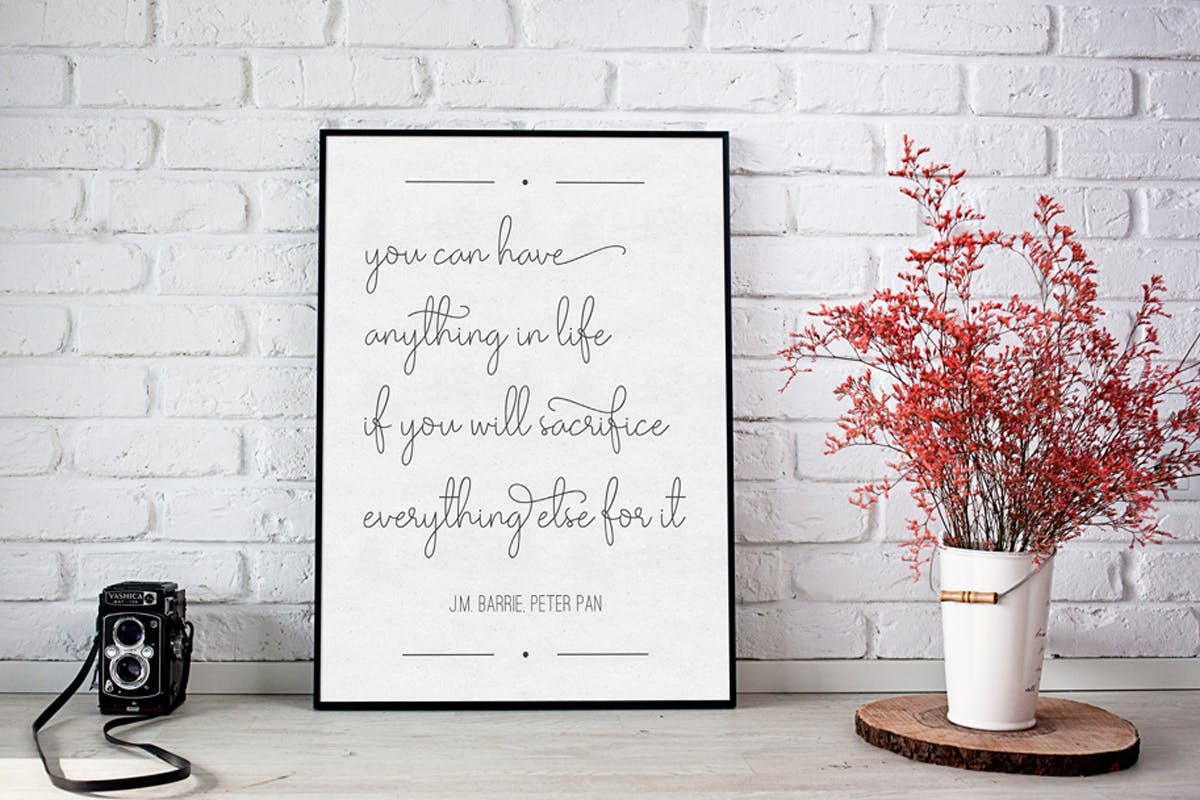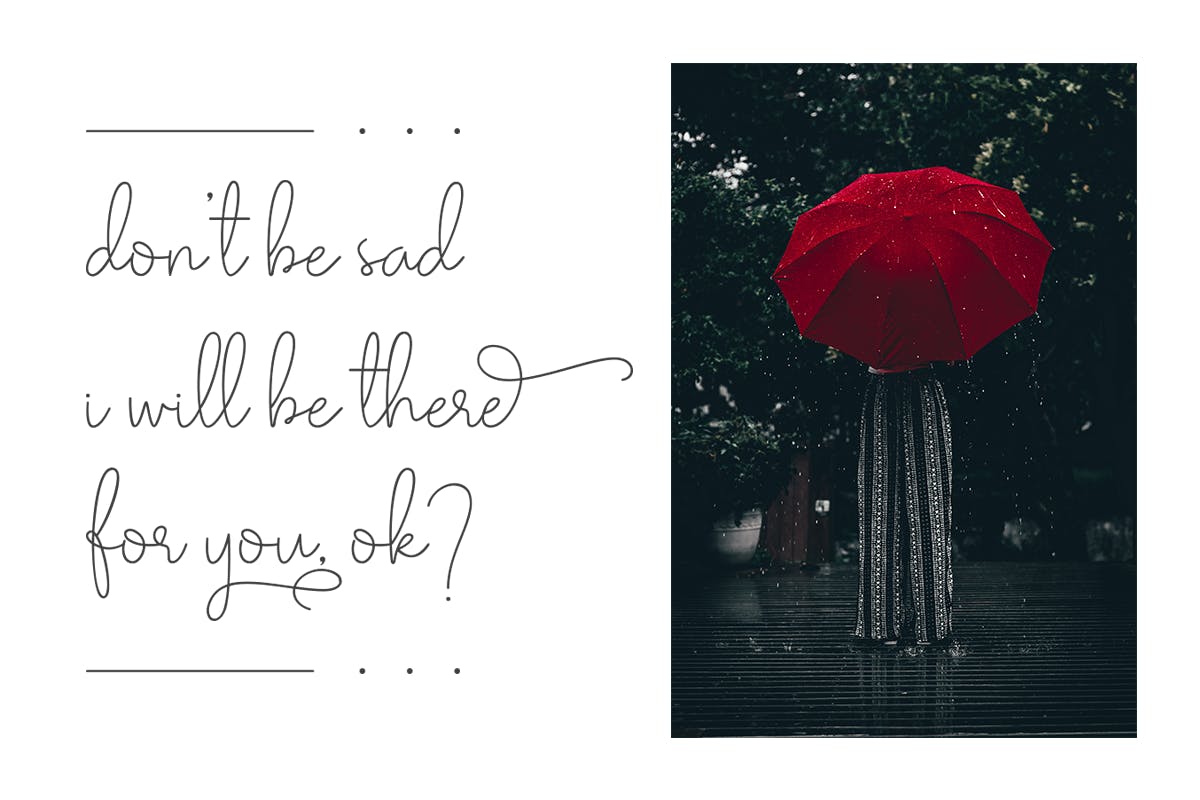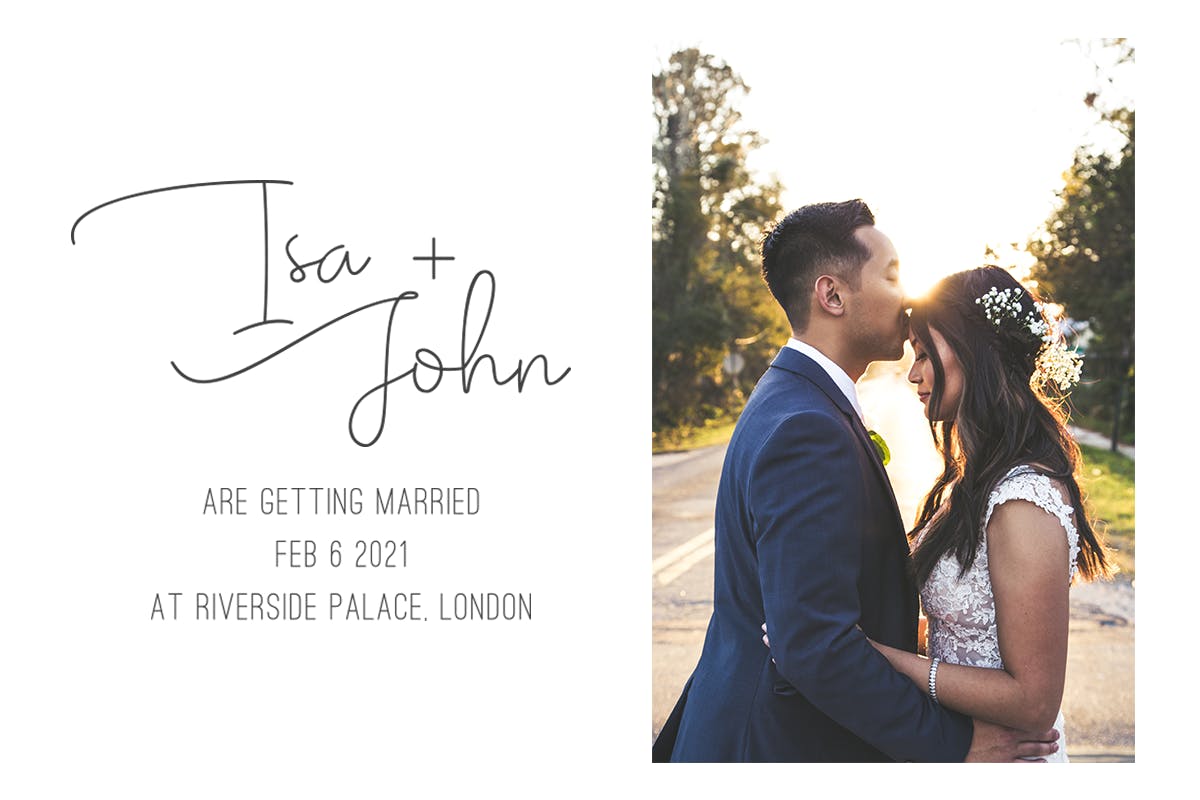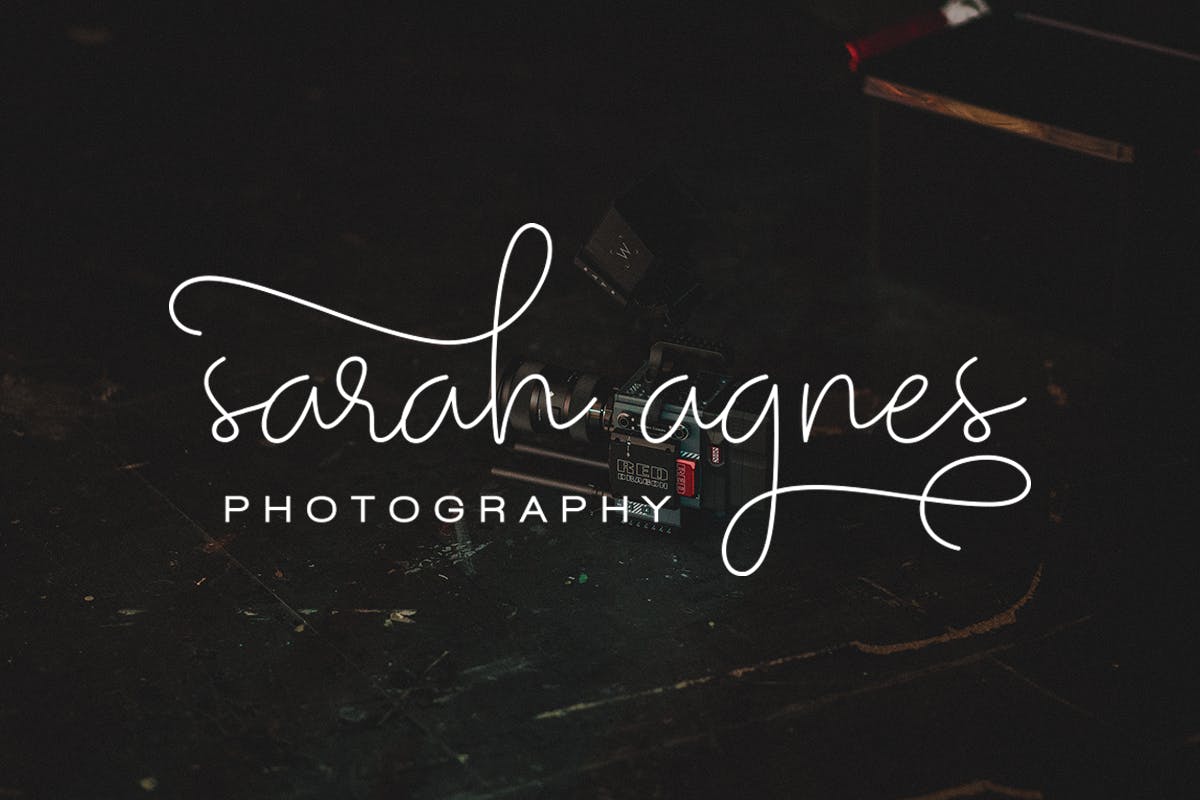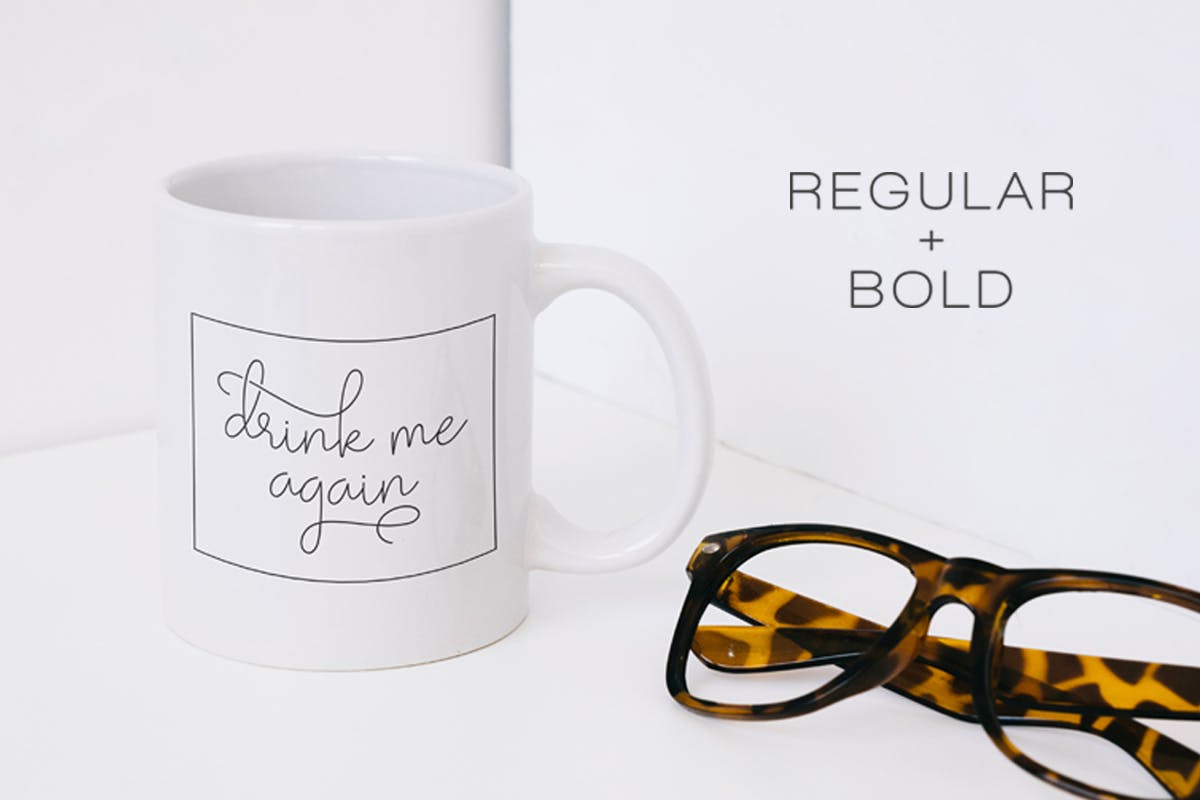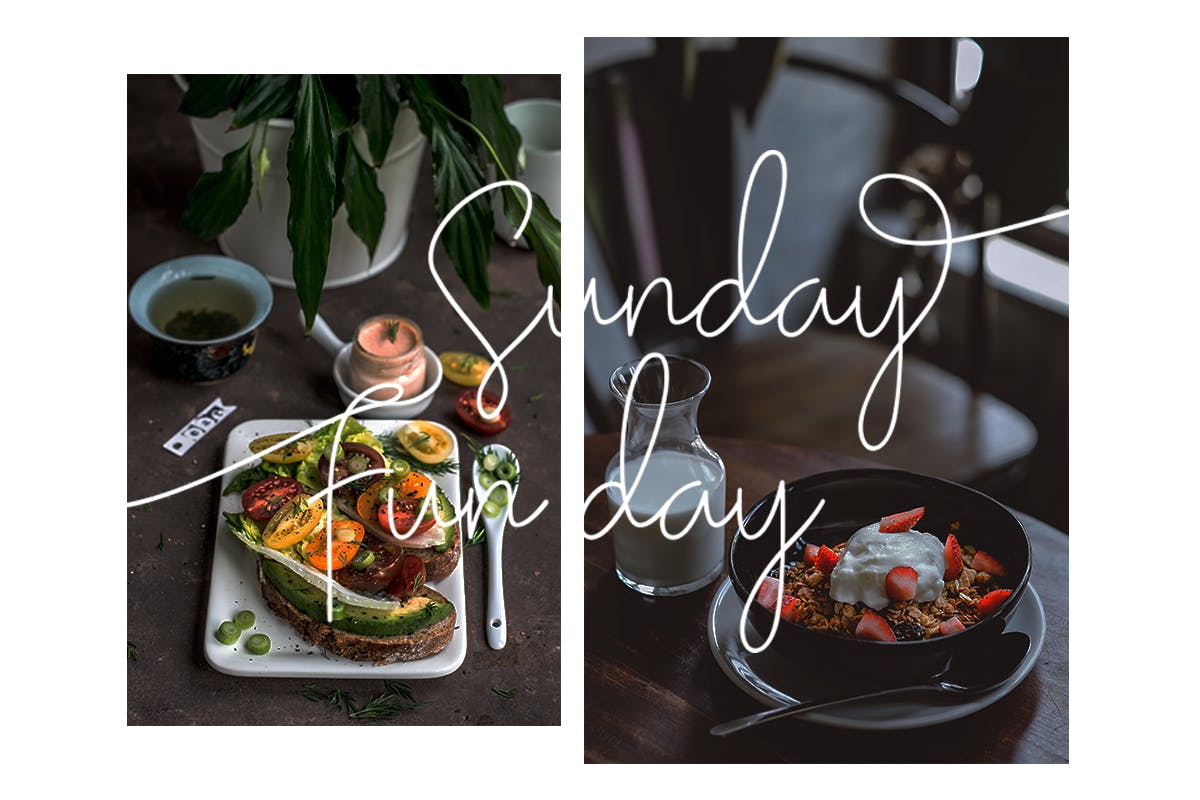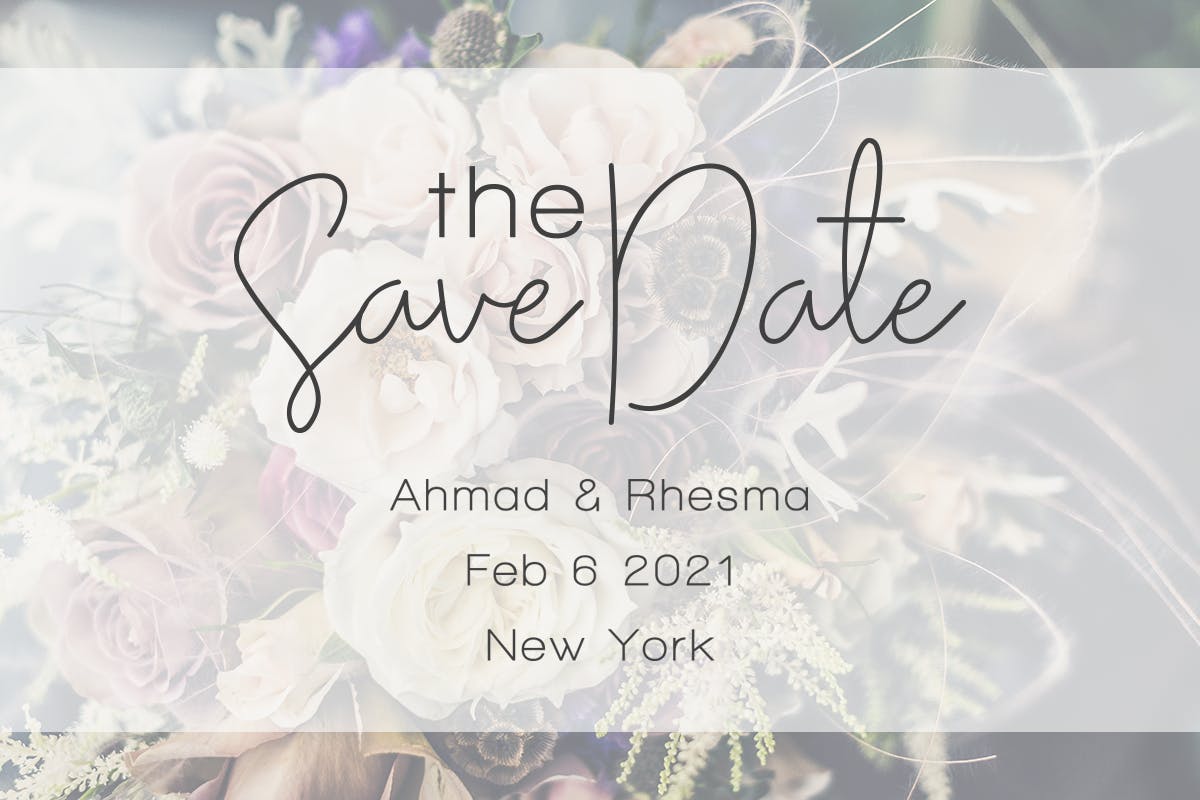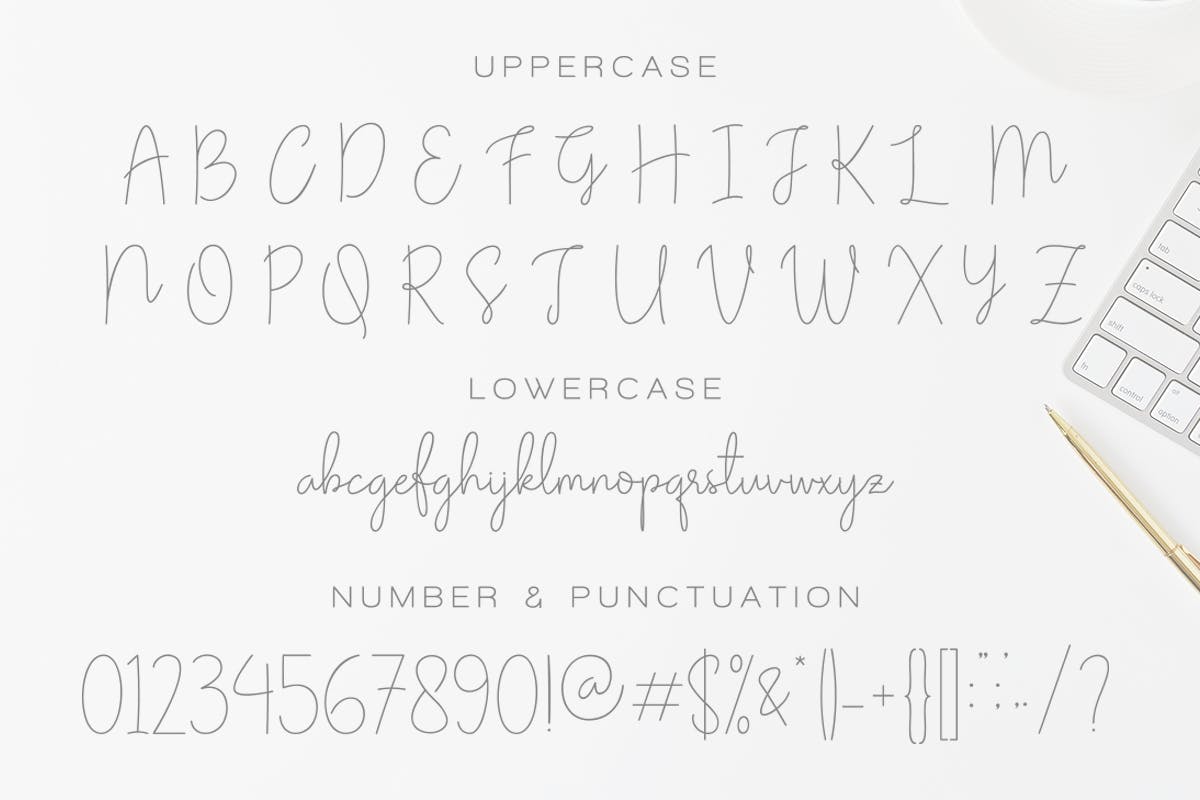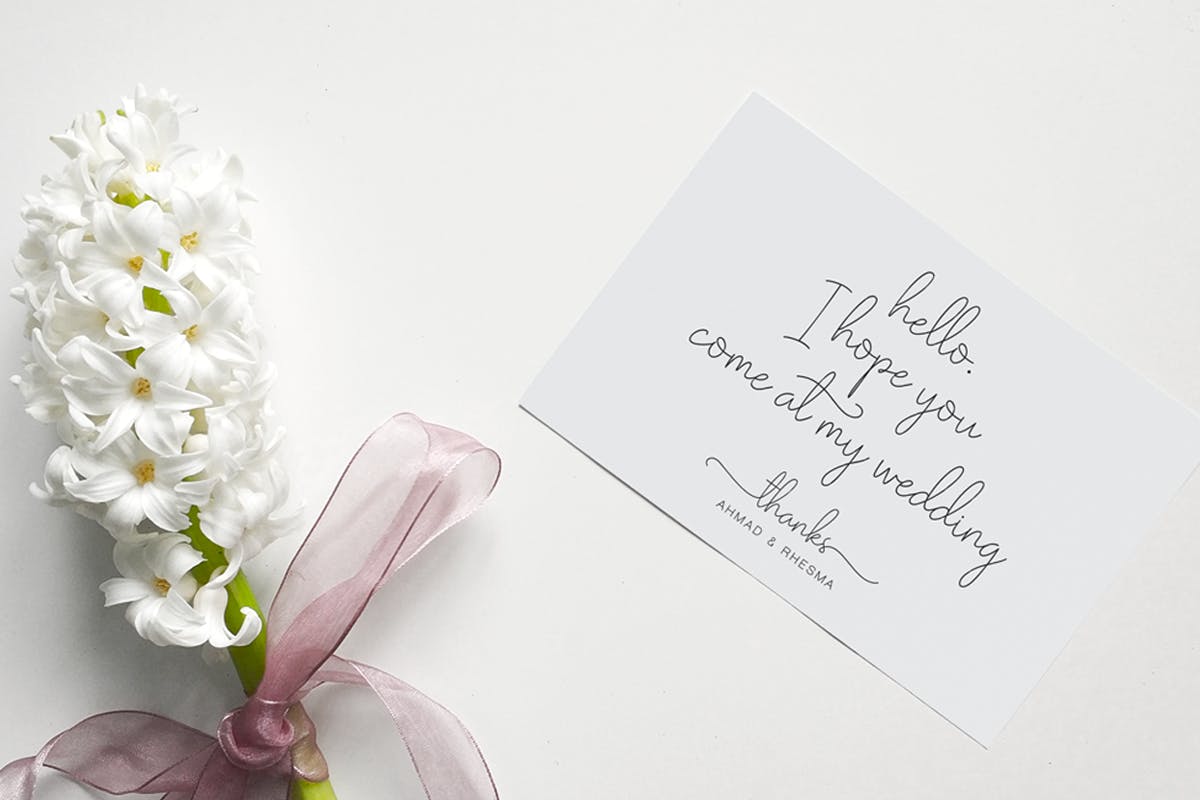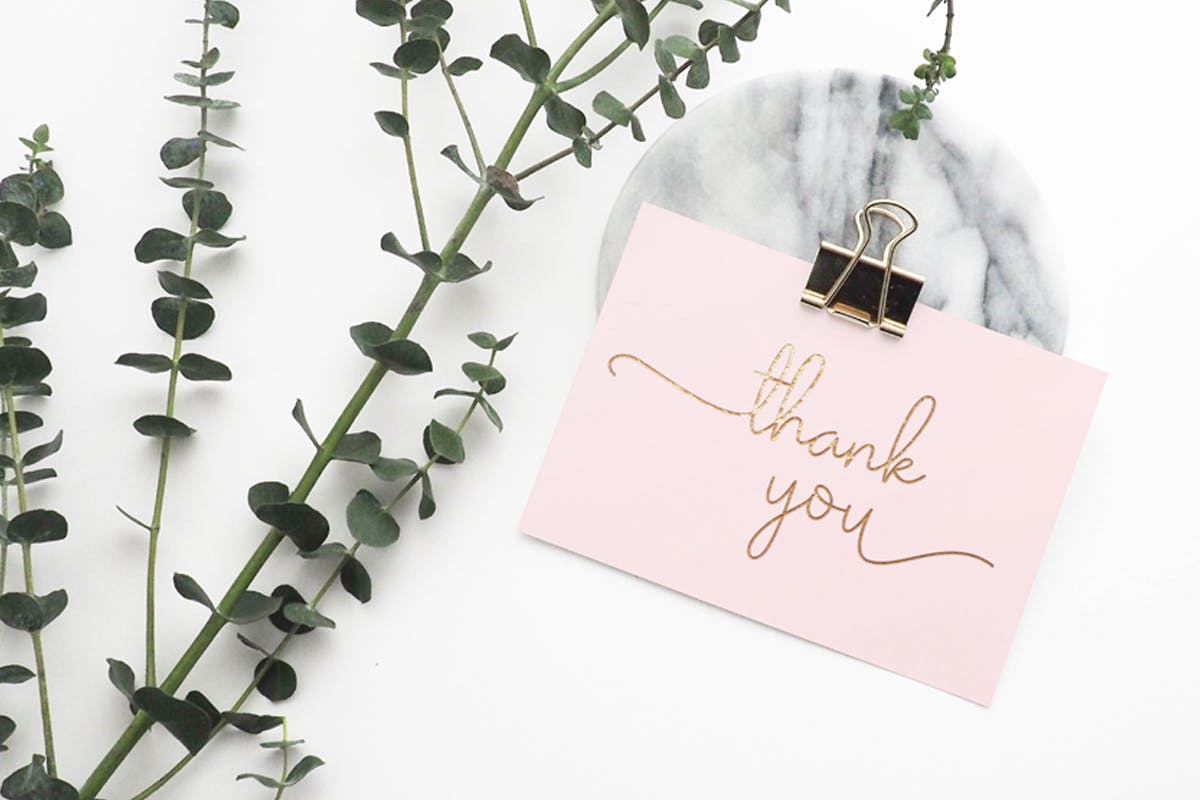
معرفی فونت جدید و شیک اولیویا!
فونت اولیویا یک فونت کالیگرافی مدرن است که بر اساس مدل مونو لاین طراحی شده و دارای جریانی پیچیده و زیبا میباشد. این فونت دارای انواع تگها و گلیفهای متفاوت است و برای برندینگ، لوگو، دعوتنامههای عروسی، یادداشتها، فنجانها، ماگها و کارتهای تبریک و بسیاری دیگر مناسب است.
فونت اولیویا شامل مجموعهای بزرگ از حروف بزرگ و کوچک زیبا، نسخههای معمولی و بولد، اعداد و نشانهگذاری است که با جریانی زیبا در حروف بزرگ و کوچک ارائه میشود. همچنین میتوانید طراحیهای زیبا را با سواشهای دلخواه خود تغییر دهید.
این فونت دارای بافتی نرم است، بنابراین برای انواع تکنیکهای چاپی ایدهآل بوده و میتوانید از آن برای گلدوزی، طلا کوبی و غیره استفاده کنید.